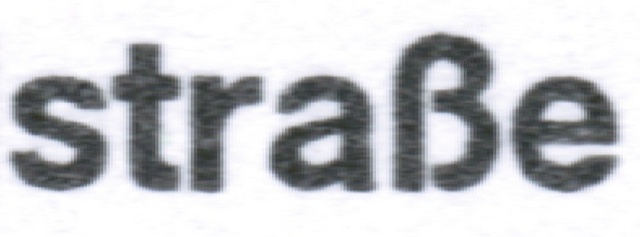
ich bräuchte mal wieder eure Hilfe bei der Suche der Schrift in der Grafik. Auf den ersten Blick mag es ganz normal wie Arial aussehen, aber achtet bitte auf das "ß" besonders. Das sieht bei Arial nicht so aus. Ich habe auch nochmal den direkten Vergleich zu Arial mit dargestellt (siehe 2. Grafik).